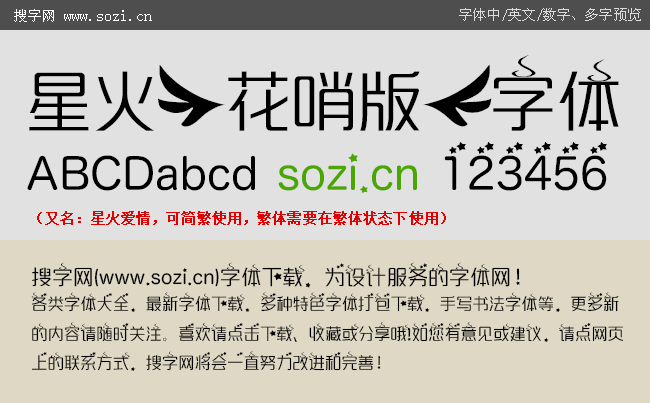
星火花哨版字體
搜字網(wǎng)給大家提供一款星火愛情字體手機(jī)中文字體下載。這款手機(jī)字體是將文泉驛微米黑的個(gè)別字體筆畫用可愛的卡通圖案進(jìn)行替換。文泉驛微米黑是一款應(yīng)用于藝術(shù)設(shè)計(jì)方面的中文簡體漢字,又名文泉驛等寬微米黑,該字體偏粗,字形大方得體,加入了卡通圖案后增添了趣味性,特別適合喜歡手機(jī)字體個(gè)性一些的朋友在手機(jī)上安裝使用。